안병국의 웹타이포그래피 – 손글씨체와 캘리그라피의 웹디자인 활용(2)
캘리그라피나 손글씨를 웹사이트 디자인에 활용하는데 있어 무엇보다 관심을 기울여야 할 부분은 글자의 개별적인 형태나 느낌이 아닌 디자인의 전체적인 조화라 할 수 있다. 사이트에서 전달하고자 하는 메시지나 사이트를 이용하는 타깃, 그리고 전달하고자 하는 콘텐츠의 내용에 따라 글씨의 형태나 질감, 색상이 정해져야 하기 때문이다. 즉, 무조건적인 캘리그라피나 손글씨의 동경에서 벗어나 조화와 균형이라는 측면에서 좀 더 신중하게 접근할 필요가 있다는 것이다.
대부분이 감성적 접근만을 중요시 한 채 세부적인 디테일을 소홀히 하는 경우가 많은데 이는 디자인 완성도를 떨어트리는 원인이 되기도 하며 디자인의 기능을 저해 시키는 이유가 되기도 한다. 따라서 캘리그라피나 손글씨를 활용함에 있어서 우리가 폰트를 선택하듯 전체 디자인의 콘셉트를 대변할 수 있는 글씨를 올바르게 사용하는 것이 무엇보다 우선시 되어야 함을 잊지 말아야 한다.
좋은 글씨와 잘 쓴 글씨
캘리그라피란 대체로 먹과 붓을 이용한 서예적인 표현 방법을 일컫고 있으며, 대다수의 캘리그라피 역시 먹과 붓을 이용해 만들어 지고 있는 것이 사실이다. 그렇기에 일반인들이 생각하는 캘리그라피는 한글을 쓰는 서예가 가장 적절한 표현인지도 모르겠다. 그래서 캘리그라피를 배우는 것과 서예를 배우는 차이에 대해 많이 이들이 혼동을 느끼게 될 수 밖에 없다. 그렇다면 영문이나 한글이 아닌 한자를 쓰는 것은 캘리그라피일까 서예일까? 또 먹과 붓이 아닌 다른 재료를 이용하여 한자를 쓰는 것은 캘리그라피일까 서예일까? 단순히 재료나 기법만의 접근으로 이를 구분하는 것은 무의미 하다고 할 수 있다. 굳이 먹과 붓을 활용하지 않더라도 캘리그라피가 될 수 있으며, 서예를 배우지 않더라도 누구나 캘리그라피를 할 수 있는 것이 바로 캘리그라피이다.
서예는 주로 글자 자체만을 놓고 심미적인 부분과 조형성을 추구하는 경향이 높지만 캘리그라피는 글자 자체만의 조형성이 아닌 글자의 의미가 글자의 형태나 질감을 통해 어떻게 표현되었느냐가 가장 중요한 부분이라 할 수 있다. 즉, 글씨 자체의 심미성이 아닌 전달하고자 하는 메시지를 효과적으로 전달하고 있느냐가 캘리그라피에 있어 가장 핵심적인 내용이라 할 수 있기에 굳이 붓과 먹을 사용하지 않더라도 이러한 부분을 고려해 직접 쓴 글자라면 모든 것이 캘리그라피가 될 수 있다고 생각한다. 따라서 서예에서 말하는 잘 쓴 글씨보다 콘셉트와 메시지를 보다 효과적으로 전달해 줄 수 있는 좋을 글씨가 좋은 캘리그라피라 할 수 있다. 그리고 그런 글씨를 쓸 줄 아는 디자이너가 좋은 캘리그라퍼라 할 수 있겠다.
캘리그라피에서 주로 먹과 붓을 사용하는 이유도 다름 아닌 바로 이 이유에 있다고 볼 수 있다. 먹과 붓을 이용하게 되면 먹의 농담에 따라 다양한 질감을 만들어 낼 수 있고 붓의 획에 따라 갈필처럼 거친 선을 만들어 낼 수도 있다. 또한, 글자에 여러 굵기의 표현이 가능해져 다양한 메시지를 지닌 글자의 형태나 질감을 통해 표현하는 것이 용이하다. 서예에서 활용하는 먹과 붓을 사용하는 주된 이유이기도 하다. 다른 재료들을 활용하여 자신이 표현하고자 하는 메시지를 효과적으로 표현할 수 있는 방법이 있다면 그것 역시 좋은 캘리그라피가 될 수 있다.
특히 웹디자인에 있어 캘리그라피를 다를 때 더 주의해야 하는 것은 어떤 디자인 분야보다 전략적인 부분을 중시하고 전체적인 조화와 균형을 중시하기 때문이다. 잘 쓴 글씨 보다는 좋은 글씨를 사용하는 디자인적 안목을 요구 받게 된다.
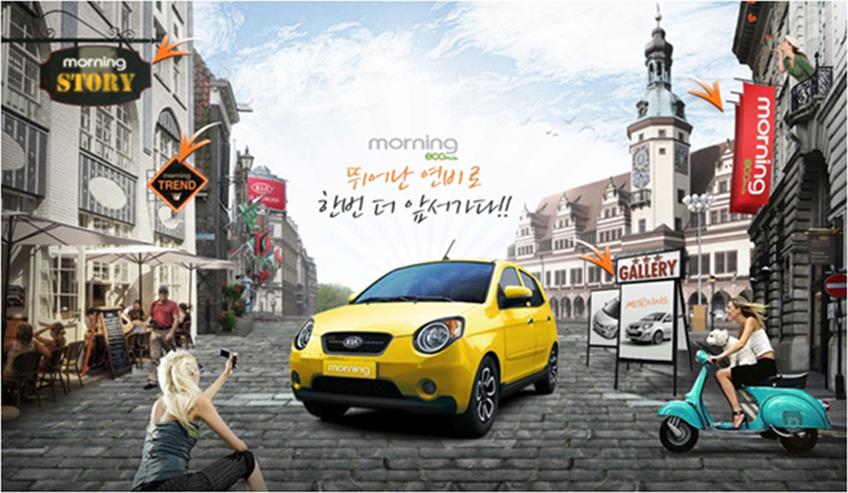
위 사이트는 기아자동차의 ‘morning’ 프로모션 사이트다. 여성을 타깃으로 감성적인 부분에 어필하기 위해 봄날체로 타이틀을 장식했다. 봄날체가 지닌 손글씨체로의 완성도나 심미성이 매우 높아 다른 폰트들 보다 메시지를 전달하는 데 있어 효과적이고 디자인의 완성도를 높이고 있지만 다소 아쉬운 부분이 있다면 전체적인 디자인적 조화라는 관점에서 높은 점수를 주기에는 아쉬운 점이 한 가지 있다.
전체 화면의 디자인을 보면 유럽의 거리를 배경으로 자유분방한 여성들이 자동차에 관심을 갖고 있는 모습을 표현하고 있다. 자동차 뷰(view) 역시 아래에서 위로 촬영된 화면을 사용해 자동차의 디자인을 강조하고 있다. 하지만 타이틀로 활용된 봄날체는 이 콘셉트와 완벽하게 일치한다고 보기는 어렵다. 봄날체가 가진 특징은 손글씨로의 감성적인 부분도 있지만 선의 형태가 곡선적인 부분이 많고, 전체적으로 굵기가 얇기 때문에 활동적이거나 역동적인 여성의 심리를 표현하기 보다는 순수함이나 서정적인 부분에 표현하는데 더 적합한 글씨체라 할 수 있기 때문이다.
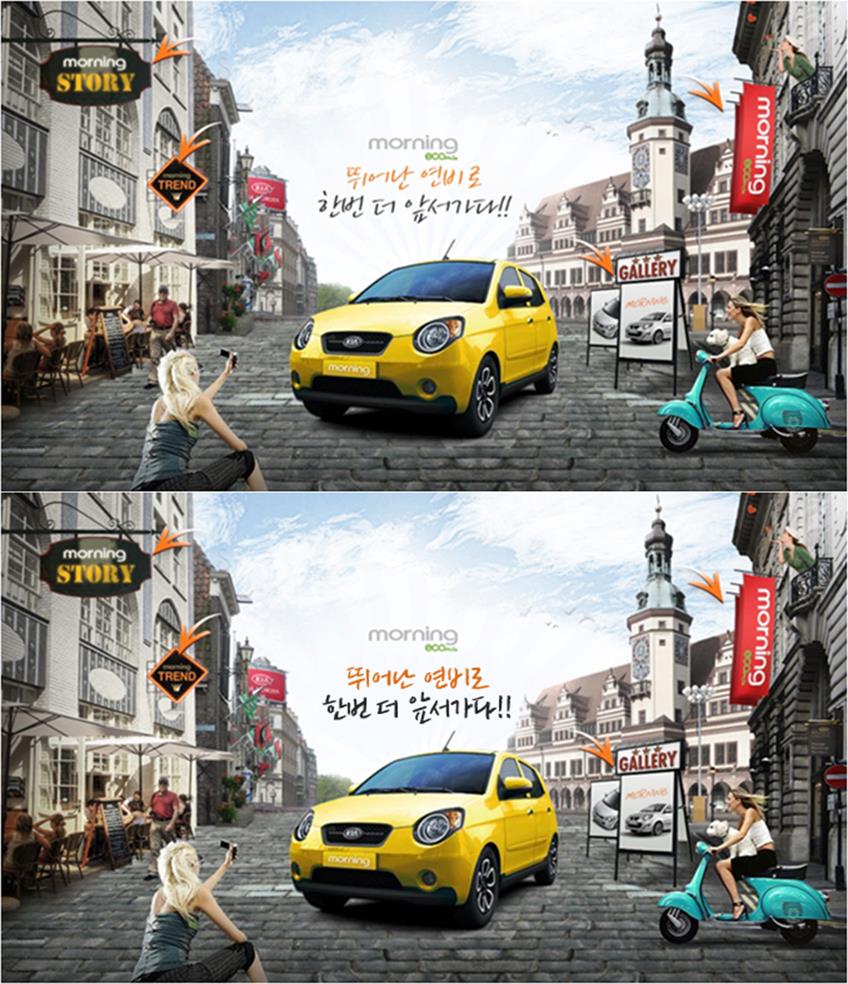
타이틀을 백종열체로 바꿨을 때(아래)
비교를 위해 원본 타이틀을 백종열체로 바꿔 배치해 보았다. 두 그림을 보면 앞에서 말한 차이를 쉽게 느낄 수 있을 것이라 생각된다. 두 글자체 모두 잘 쓴 글씨이기는 하지만 모닝 사이트에 더 잘 어울리는 서체(손글씨)는 백종열체다. 이유는 백종열체의 경우 봄날체에 비해 곡선의 느낌보다는 직선의 느낌이 강하고 글자 굵기가 더 굵어 작지만 강한 자동차를 표현하기에 더 효과적이기 때문이다. 두 글자 모두 감성적인 부분을 중시하고 있어 감성적인 부분만을 따진다면 두 글자 모두 좋은 글씨라 할 수 있지만, 모닝 사이트에서만큼은 전체적인 비주얼 콘셉트나 전달하고자 하는 메시지에 백종열체가 더 적절해 보인다.
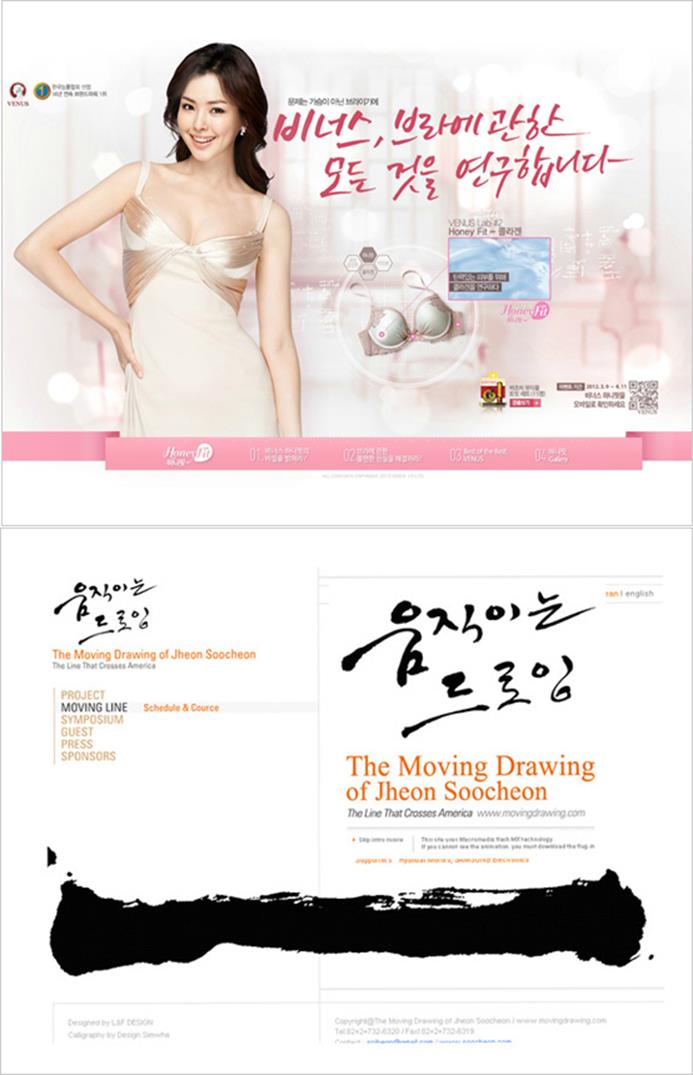
비너스 프로모션 사이트와 움직이는 드로잉 전시 프로모션 사이트에 사용된 캘리그라피는 서로 비슷한 느낌으로 쓰여 있다. 글씨만 떼어 놓고 보면 캘리그라피적인 느낌을 둘 다 잘 살린 멋스러운 글씨들이지만 이 둘은 전혀 다른 콘셉트를 지닌 사이트라 볼 수 있다. 비너스 사이트는 여성적인 면과 여성의 신체적인 곡선의 아름다움을 담고 있는 반면 아래 움직이는 드로잉은 붓의 터치를 강조하고 역동적인 느낌을 전달하고 있는 사이트라 할 수 있다.
즉, 비너스 프로모션 사이트의 캘리그라피는 글씨 자체의 심미적인 부분을 봤을 때 매우 잘 쓴 글씨라 할 수 있지만 사이트의 콘셉트와 어울리는 좋은 글씨라 할 수는 없다. 그래서 웹디자인에 사용된 캘리그라피적인 관점에서는 높은 점수를 주기 어렵다. 이처럼 1차원적으로 캘리그라피나 손글씨가 지닌 감성적인 접근만을 중시하고 무조건적으로 캘리그라피나 손글씨를 웹디자인에 활용하는 것은 바람직하지 못하다.
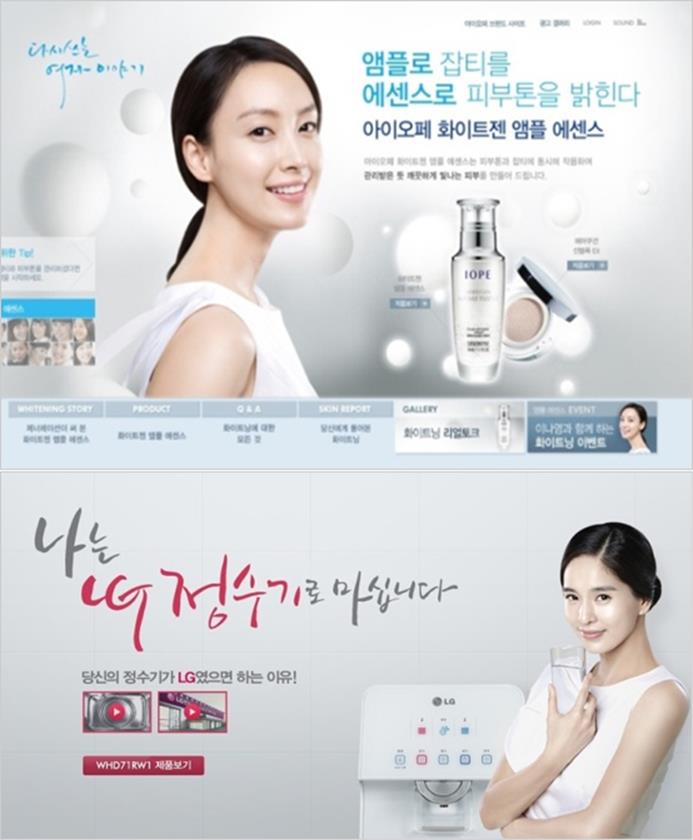
아이오페 프로모션 사이트나 LG정수기 프로모션 사이트 둘 다 단아한 여성미를 강조하기 위한 콘셉트가 강하다. 깨끗하고 기능적인 부분을 강조하기 위해 아이덴티티 색상만을 달리하고 하나는 로고로 하나는 타이틀로 은색(silver) 배경에 캘리그라피를 사용하고 있다. 하지만 ‘조화’라는 부분을 염두에 두고 봤을 때 두 사이트의 글씨가 주는 완성도나 느낌은 확연한 차이를 보인다.
우선 아이오페 브랜드 사이트에서는 글자들의 전체적인 과장보다는 여자이야기 부분에서 ‘여’자 부분만 세로로 길게 빼 여성의 단아한 미를 강조하고 있는 반면 LG정수기에서는 색상의 변화나 글자들의 크기 변화가 매우 심하게 나타나고 있다. 또한 굵기 변화가 모음이나 자음 단위가 아닌 모음이나 자음 그 안에서 이루어지다 보니 아이오페 브랜드 사이트에서 사용된 캘리그라피에 비해 자연스러움이 많이 떨어져 보이는 것이 사실이다.
이는 콘셉트를 비교해 봤을 때 많은 변화보다는 자연스러운 율동감을 지니면서 여성의 아름다움을 강조할 수 있는 캘리그라피가 더 효과적이라는 점을 보여주고 있다.
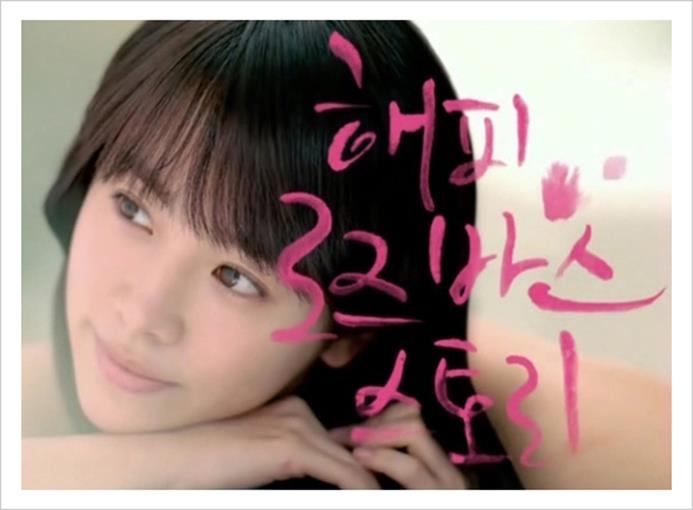
해피로즈바스 스토리의 경우도 캘리그라피에서 일반적으로 사용하는 검정색으로 처리하지 않았지만 립스틱의 색상과 질감을 활용해 젊은 여성의 느낌과 욕실에 있는 여성의 심리를 잘 표현하고 있다. 또한 글씨 형태 역시 끊기지 않고 자연스럽게 이어지는 형태를 하고 있다. 립스틱이이라는 질감과 잘 맞아 떨어지고 있다. 굳이 캘리그라피를 표현함에 있어 먹과 붓을 활용하지 않더라도 전체적인 느낌과 디자인 콘셉트를 명확히 살린 글씨라면 좋은 캘리그라피가 될 수 있다는 것을 위 사례를 통해 알 수 있다.
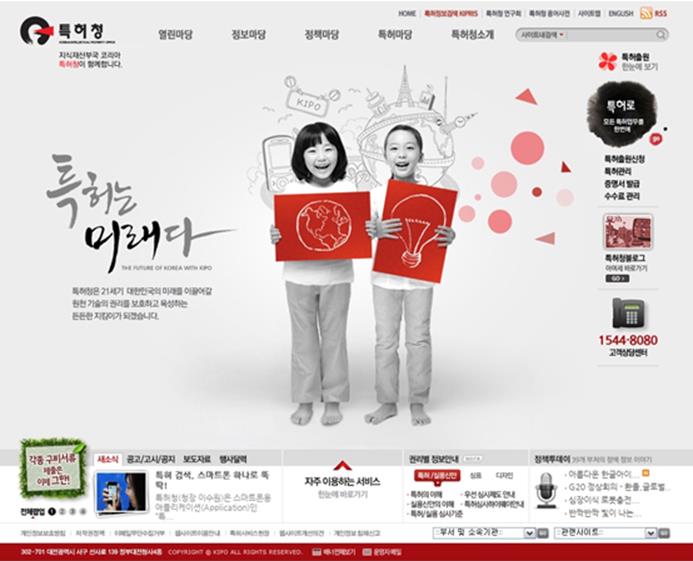
마지막으로 특허청 사이트에 사용된 캘리그라피를 살펴보자. 글씨에서 느껴지는 필력이나 느낌이 매우 좋은 느낌이다. 하지만 아이들을 모델로 하였고 발명이라는 재미적인 부분을 강조하고자 했다면 다른 방식의 캘리그라피를 활용하는 것이 더 효과적이지 않았을까 하는 아쉬움이 있다.
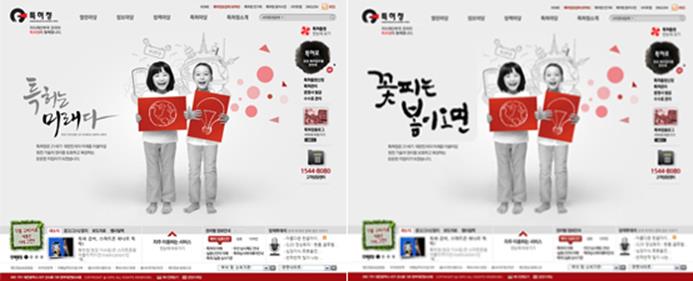
손글씨를 바꿨을 때(오른쪽)
기존 특허청 사이트에 영화 <꽃피는 봄이오면>에서 타이틀로 활용되었던 캘리그라피를 실험 삼아 대입시켜 보았다. 비록 영화에 사용되었던 캘리그라피이지만 원래 사이트보다 훨씬 더 사이트의 콘셉트를 잘 전달하고 있음을 알 수 있을 것이다. 우선 글자의 긁기가 두껍고 귀엽게 느껴지는 형태를 띄고 있어 ‘아이들’이라는 요소와 ‘재미’라는 콘셉트에 더 잘 맞아 떨어지고 있기 때문이다.
지금까지 살펴봤던 것처럼 웹디자인에서 캘리그라피를 활용함에 있어 잘 쓴 글씨보다는 좋은 글씨를 선택하는 것은 마케팅이나 디자인 전략 차원에서 굉장히 중요하다. 대부분의 사례를 붓글씨를 활용한 캘리그라피를 중점적으로 살펴보았지만 굳이 붓글씨를 활용하지 않았다 하더라도 아래 두 사례처럼 웹사이트에 적합한 캘리그라피나 손글씨 사례를 많이 찾아 볼 수 있다.
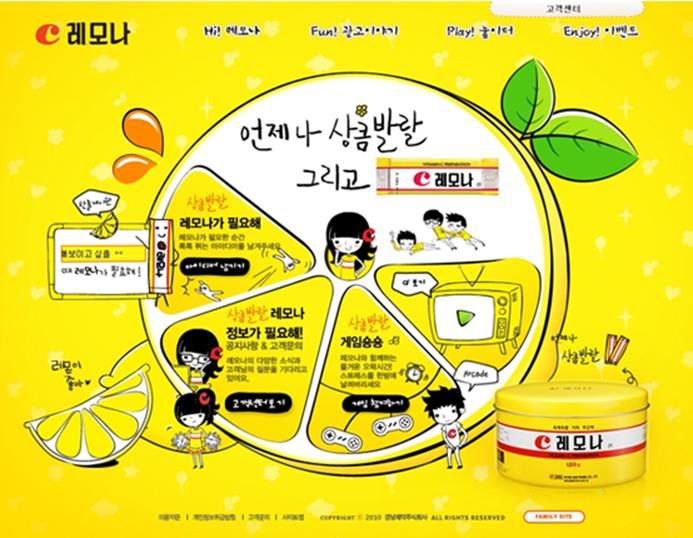
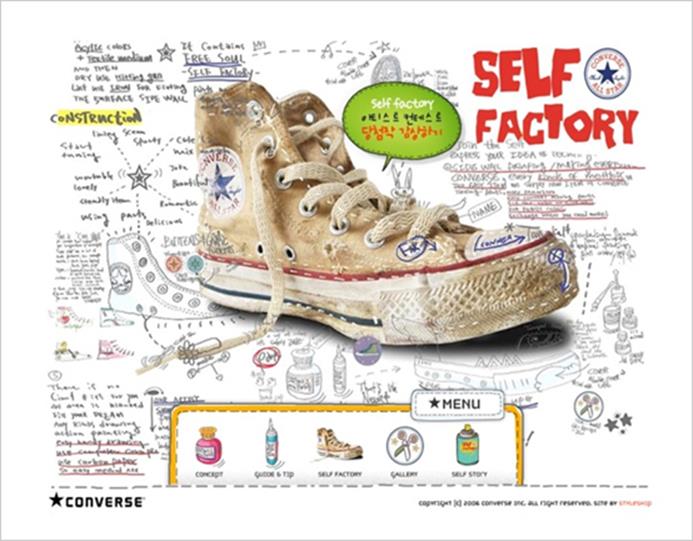
위 레모나나 컨버스 프로모션 사이트는 붓을 활용하지 않았지만 타깃이나 콘셉트를 표현하기 위해 펜 글씨 형태로 디자인되었다. 그런데 그 어떤 붓글씨 캘리그라피 타이틀 사이트의 콘셉트를 명확히 전달하고 있다. 서예적인 관점이나 글씨의 잘 쓰고 못 씀의 관점에서 살펴 본다면 분명 잘 쓴 글씨는 아니다. 하지만 의도적으로 못 쓴 글씨를 활용하여 메시지를 전달하는 데 효과적으로 사용하고 있기에 그 어떤 명필보다 좋은 글씨라 할 수 있을 것이다.